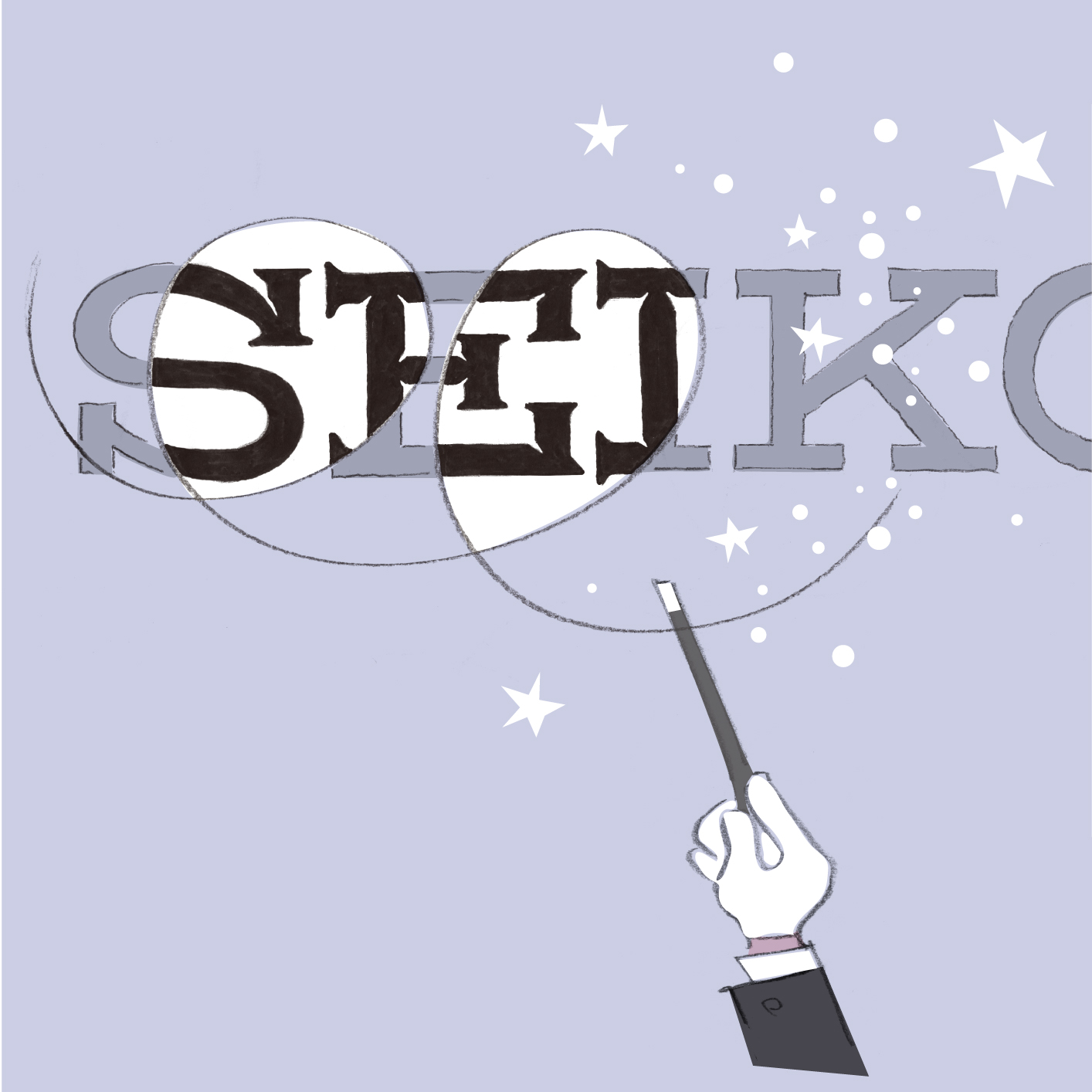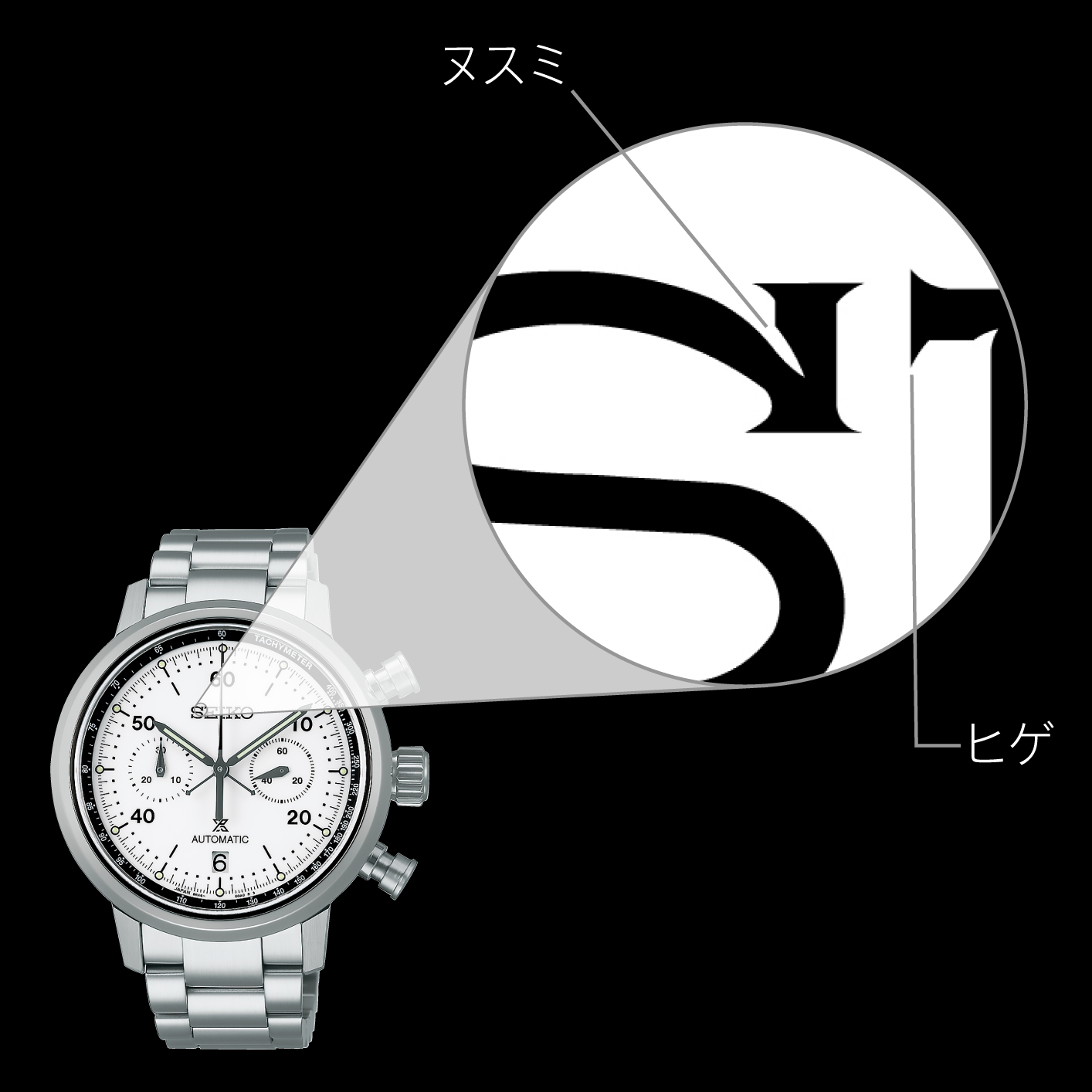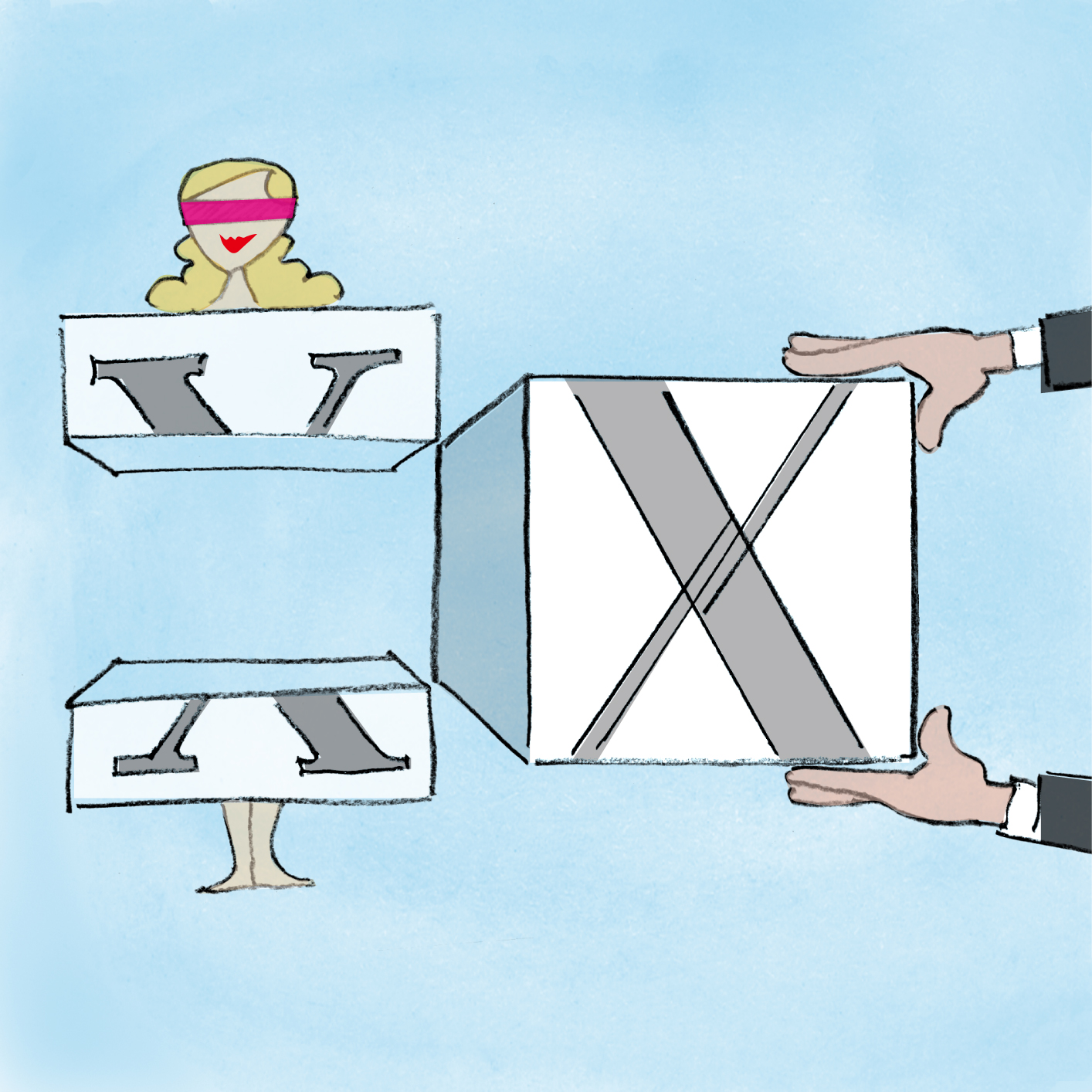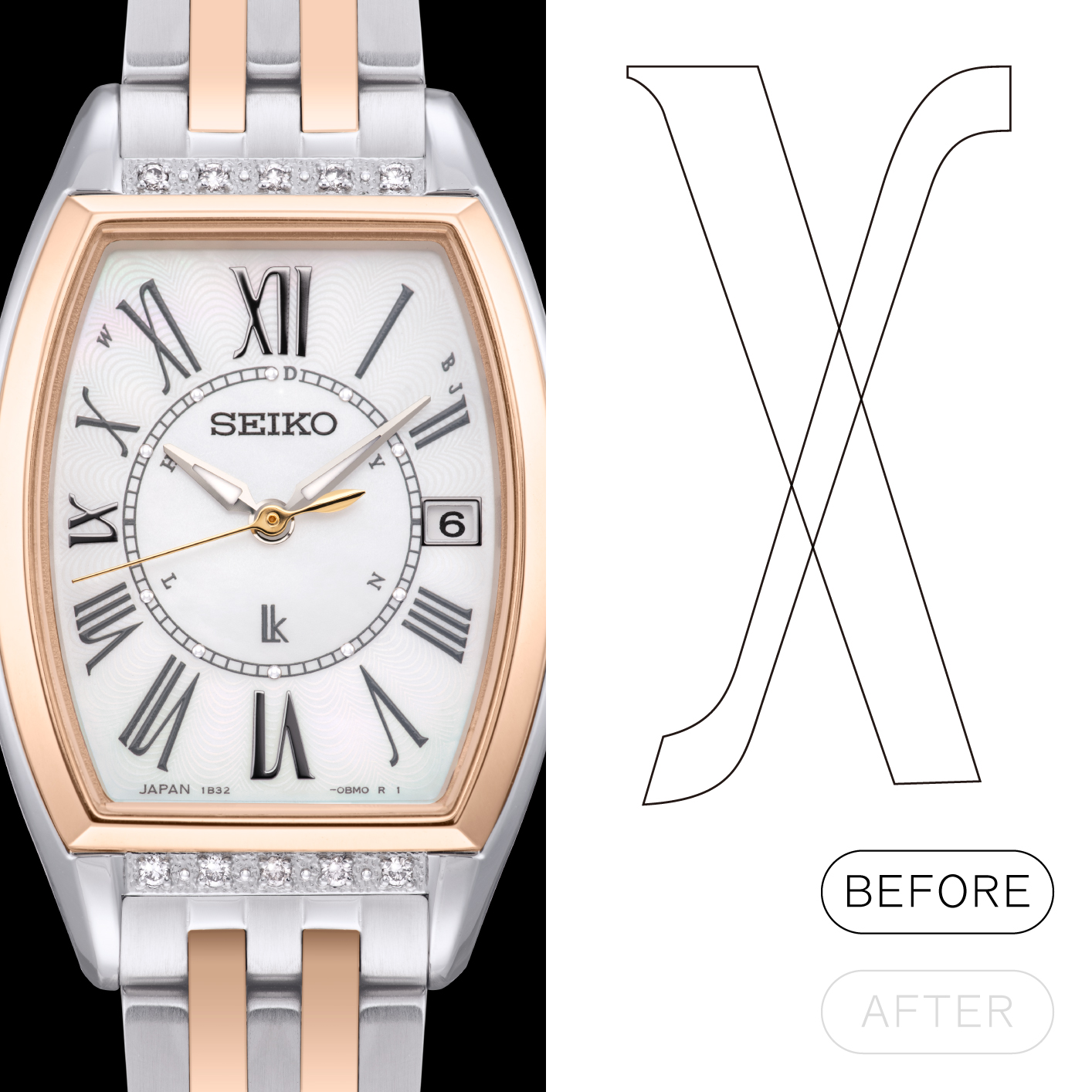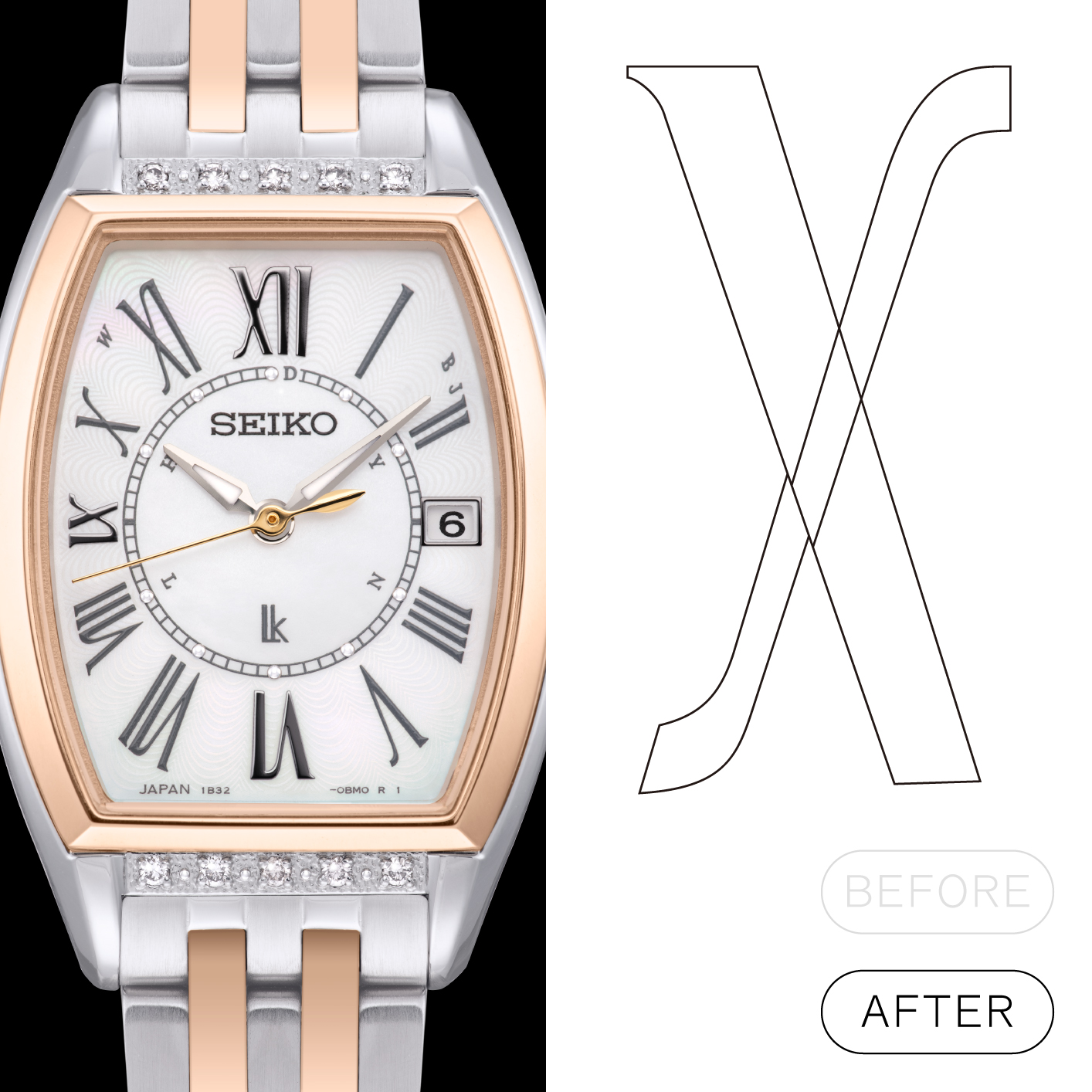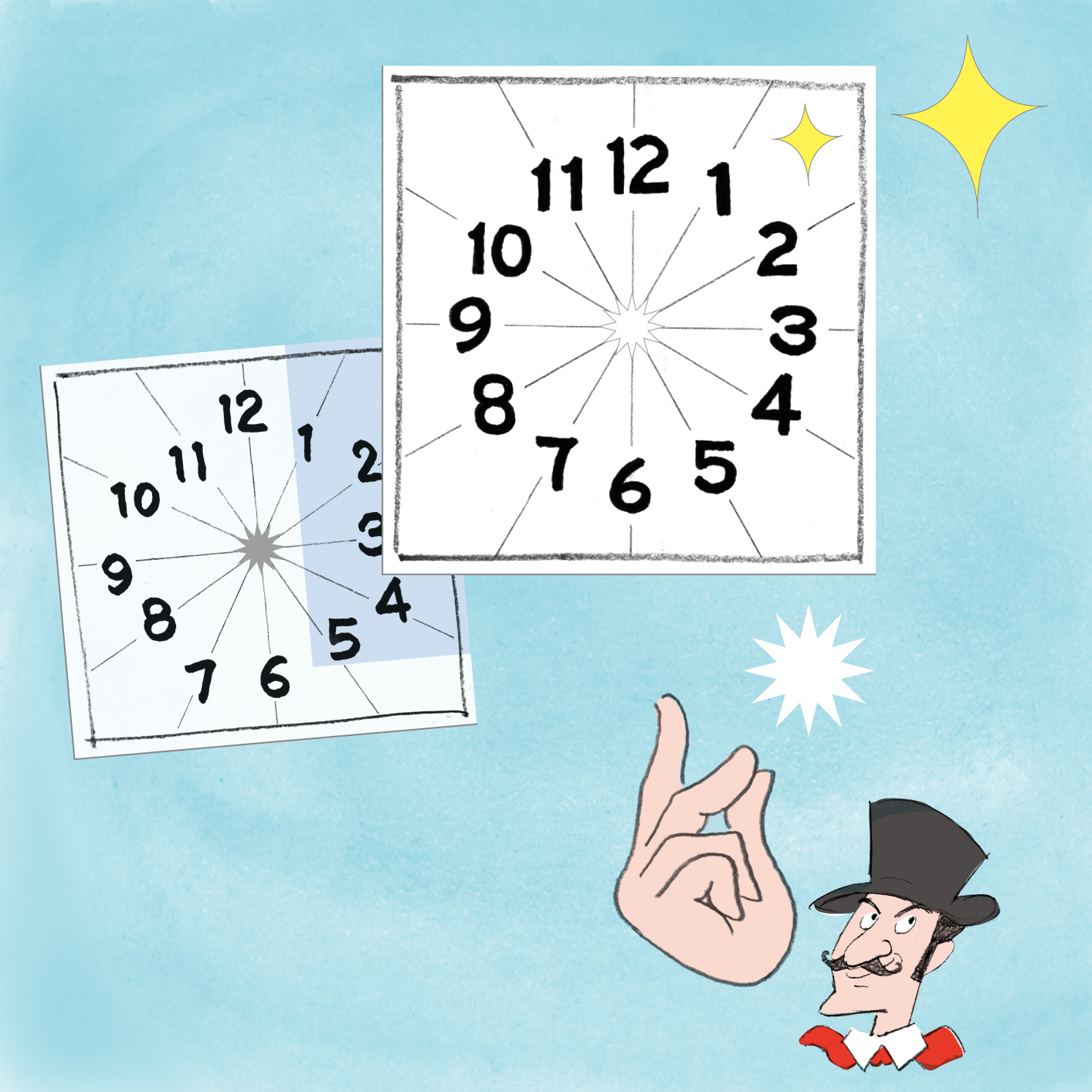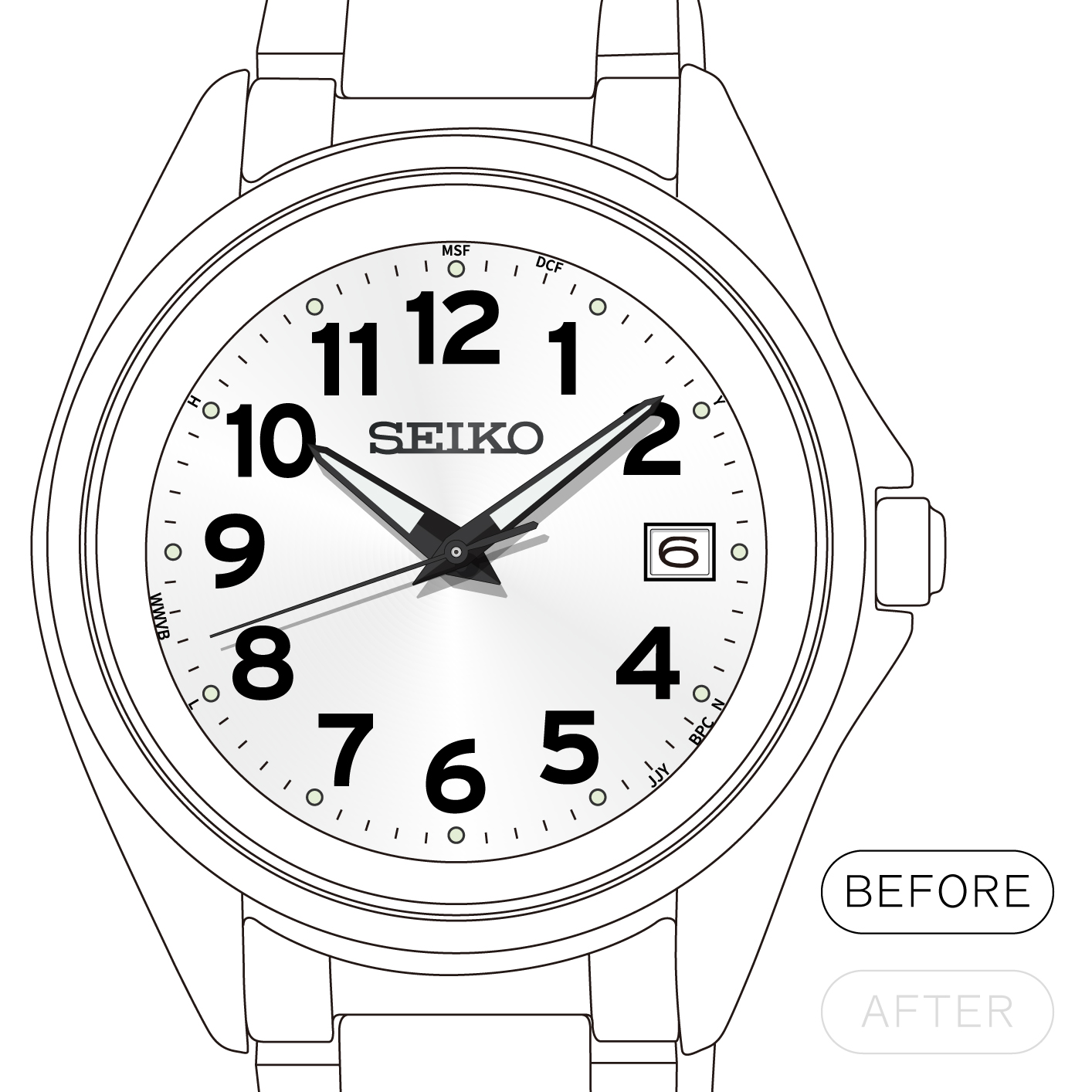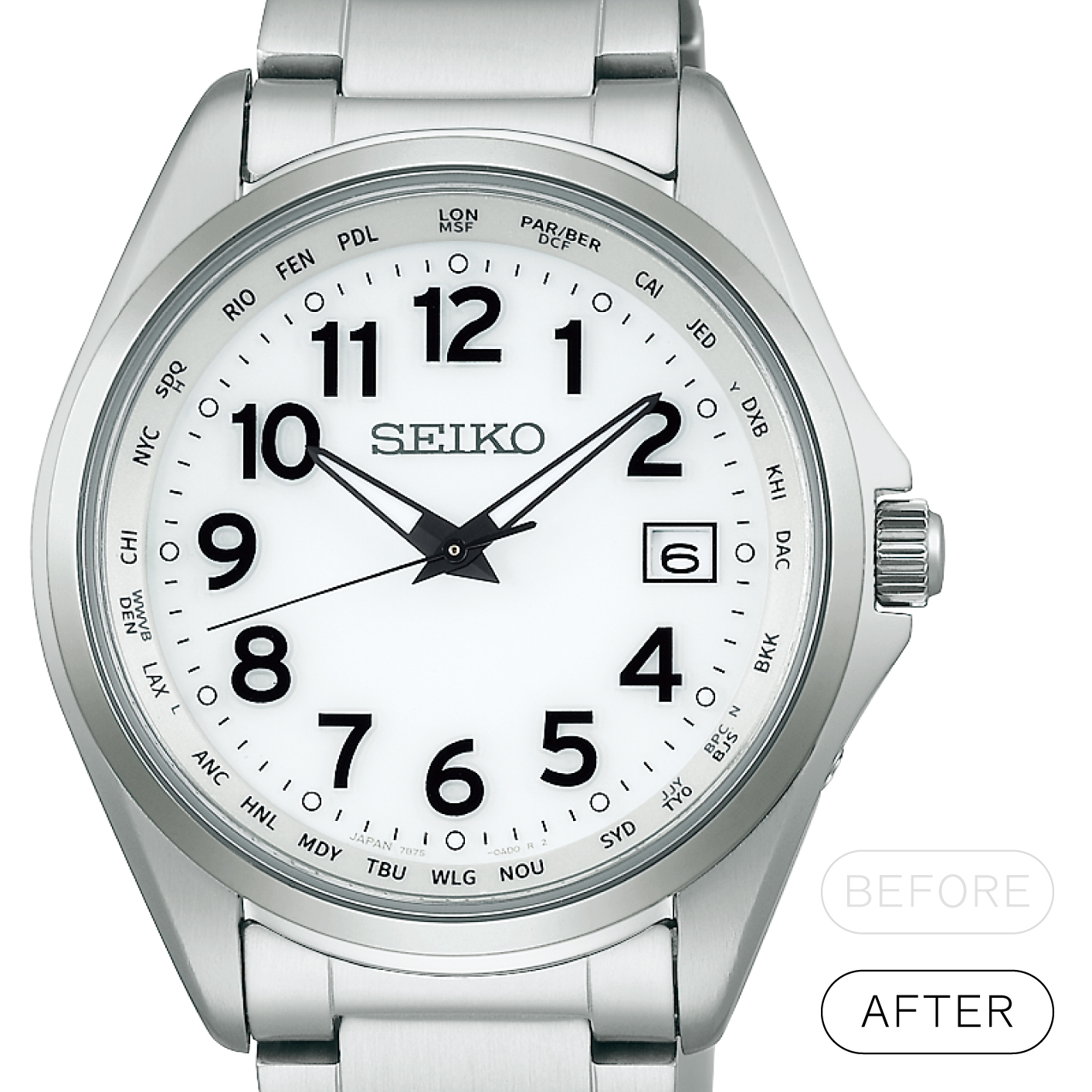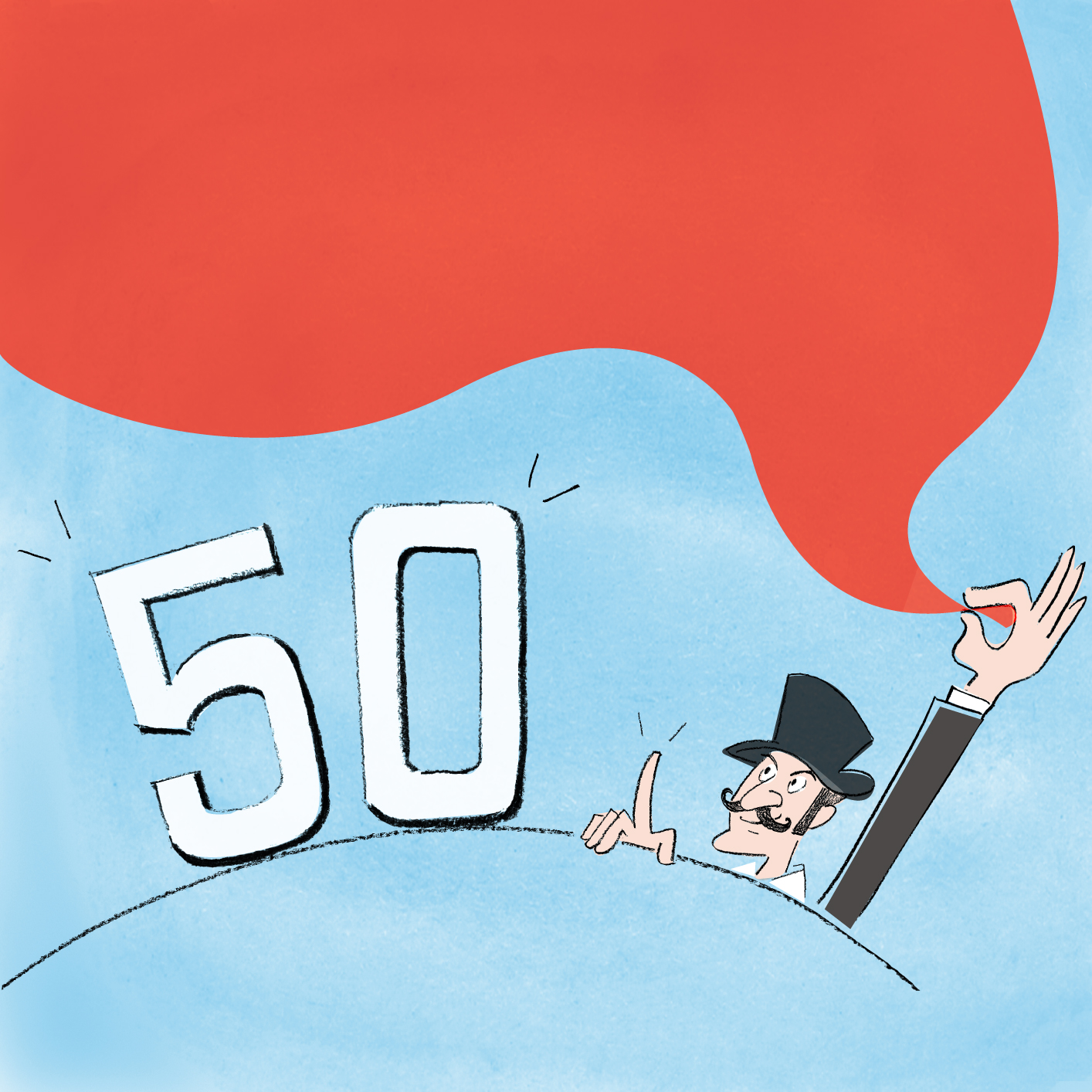
Vol.30 タネも仕掛けもございます。 「見やすさ」を支える、書体デザインの秘密。 Vol.30 タネも仕掛けもございます。 「見やすさ」を支える、書体デザインの秘密。
セイコーのウオッチのダイヤルをじっくりと眺めたことはあるだろうか。もっと言えば、ダイヤルに刻まれているインデックスや目盛りの形、さらには、そのインデックスがどういった場所に配置されているかに注意を向けたことはあるだろうか。毎日何気なく目にしている腕時計。その「見やすさ」を支えているのは、じつは書体デザインの「ある仕掛け」によるものだということは、あまり知られていないかもしれない。今回は、そのようなデザイナーの仕掛け(=技術的な工夫)の種明かしをしながら、書体デザインの知られざる秘密について紹介していきます。(2022.04.22)
セイコーの書体デザインの源流
そもそもセイコーのウオッチデザイナーの前身はダイヤルの版下職人や外装設計者でした。現在ウオッチデザイナーと呼ばれているような職種は、1956年に「生産部意匠係」として組織化した際の「意匠担当」に源流があります。それが国内初のウオッチデザイナーであったようです。
1900年から1950年代頃までのウオッチのケースは、スタンダードな2本かんのシンプルなデザインがほとんどでした。ムーブメントが定型だったためケースの構造・形状には差が少なく、バンドも店頭でユーザーが好きなストラップやブレスレットに付け替えることが多く、正規品には重きを置いていませんでした。だから必然的に、当時のデザイナーの仕事の多くは「ダイヤルデザイン」だったのです。
そんな歴史的背景もあり、セイコーのウオッチデザイナーには、ダイヤルへのこだわりがDNAとして受け継がれているのかもしれません。そこで今回は「違和感なく自然に見える」という目的のための、細部の「知られざる」技について、具体例を挙げながら詳しく見ていきたいと思います。
「見やすい文字」の、ヒミツの仕掛け
ウオッチの文字を見ていく前に、まずはブランドの顔となるSEIKOロゴを例に見てみましょう。Sの文字に注目してみると、文字の角が鋭く飛び出しているのがわかります。この部分を社内では「ヒゲ」と呼び、この処理を施すことで小さい文字でもくっきりと印刷できる効果があります。
また、縦線と曲線の境目に切れ込みのようなものが入っていることも確認できます。これは社内では「ヌスミ」といい、この処理を施すことで文字の角にキリッとした印象を与えることができます。
デザイナーは技術を駆使して、まるで魔法をかけるかのように心地よい視覚体験を生み出す。
拡大してみるとしっかりとヒゲがついているのが見て取れる。ヌスミについてもかなりの切れ込みが入っていることがわかる。
これらの技は数字にも用いられており、例えばドレッシーなウオッチによくみられるローマ数字には、よりエレガントな印象を持たせるねらいも込め、やや強めにヒゲをつけたりもします。たとえば、このルキアのローマ数字は「万年筆で書いたような」手書きの雰囲気を持たせるために、筆の運びの方向を意識して強めのヒゲをつけているのです。
そして、じつはローマ数字に見られる「X」の文字。この文字にも、おそらくふつうは気づくことのない仕掛けが施されています。その仕掛けは、クロスしている部分にあります。この「X」は細い線と太い線の交差でできているため、じつはそのままだと人間の視覚の特性上、ややズレているように見えてしまいます。そのズレを計算し、細い線が一直線に見えるような処理を施しているのです。ふつうに生活している中でこの仕掛けに気づくことはほぼ不可能でしょう。
細い線は、実は一直線ではない。種が分かればどうということはないこの小さな違いが、視覚体験には大きな違いをもたらす。
オリジナル書体がデザインされたルキア(SSVW180)。斜線の交差する部分をわずかにずらした補正をしているため、線は違和感なくまっすぐに見える。
「ふつうに見える」の、タネあかし
次に、文字の配置について見ていきましょう。ふつうに見えるということは、つまり「違和感がない」ということ。それをクリアする上で意識しなければならないのは、なんと言っても数字を12の分割の中に心地良く配置すること。ウオッチデザイナーは特に、円の形状と戦っていると言っても過言ではありません。
ここではアラビア数字のウオッチを例に見ていきます。やや間違い探し的ですが、若手デザイナーが最初に作成したレンダリングと、先輩デザイナーと共に更にそれをブラッシュアップし、最終的に商品化されたものを見比べてみてください。より心地良くアラビア数字が配置されていると思いませんか?違和感なくふつうに見える裏に、デザイナーの並々ならぬ努力と経験の積み重ねが隠れていることがわかりますね。
2枚のカードに描かれたダイヤル。一見するとどちらも同じに見えるが…。
ベテランデザイナーの助言により、わずかな違いであっても明らかに配置が整っていることがわかる。
また、回転ベゼルの表示板に配置されたアラビア数字にも仕掛けが施されています。このアラビア数字を取り出して、そのまま正体(せいたい)にしてみます。すると、2つの数字同士がやや外側に傾いていることがわかります。これも人間の目の錯覚で、アラビア数字を円周上にそのまま置くと、やや内側に、ハの字のように傾いて見えてしまうのです。その補正処理も、ふつうに見えるための欠かせないポイントのひとつなのです。
あくまでも自然に、手を加えているように見せない。それがプロの仕事と言えるのかもしれない。
わずかな数字の傾きを施しバランスのよい配置のプロスペックス(SBDC181)。お手持ちのウオッチを観察してみると、そこにも補正のテクニックが施されているかもしれない。
「そこまでやるか」な、錯視補正
せっかくですので、最後に「そこまでやるか」な錯視補正の例を見ていきましょう。ひとつ前に紹介した文字の配置は、ふつうに見えるための「なくてはならない」処理です。一方、最初に紹介した「ヒゲ」や「ヌスミ」は、より見やすくするための、いわばデザイナーのこだわりとも言えます。それが顕著に現れている例がグランドセイコーのモデルにあります。
このSBGC244を見てみると、ダイヤル上のアラビア数字だけでなく、ベゼル上の数字にもヒゲがついていることがわかります。さらには、ダイヤルリングの目盛り一つひとつにもヒゲをつけてあるこだわりよう。実際の商品を見るとその効果はかすかに感じられる程度ですが、ここにはグランドセイコーのクロノグラフらしい、研ぎ澄まされた佇まい、精緻感が表現されています。「最高のふつう」を体現する、グランドセイコーの使命感のようなものが感じられます。
用意の周到さ、細部への心配りが完成度を上げる。手品も、ダイヤルのデザインも。
ベゼルのアラビア数字はもちろん、サブダイヤルのアラビア数字にまでヒゲの処理がされている。「神は細部に宿る」を体現するモデルの一つと言えよう。(SBGC244)
使命感といえば、計測器としてのウオッチを追求した、プロスペックス SPEEDTIMERシリーズにも強い使命を感じます。SEIKOの文字にはしっかりとヒゲ、ヌスミが施され、数字や秒目盛りは最適な距離感とボリュームを考えられた配置になっています。また目盛りには細かな「線」だけでなく「点」も採用。記録を正確に計測するために、視認性と判読性をできる限り高めています。正確さが求められるプロスペックスだからこその「そこまでやるか」。というより、この場合「そこまでやるべし」なのかもしれません。
左のプロスペックス(SBEC007)は計測機器としての判読性を重視したデザイン。1954年に開発された高精度ストップウオッチ(右)から、そのデザインの思想は脈々と受け継がれている。
ウオッチデザイナーの研鑽はつづく
このような「ふつうに見えること」の裏に隠されたさまざまな仕掛けは、これまでのセイコーの歴史の積み重ねによって磨かれてきました。その中には、ルール化・定石化されているものもありますが、それをさらに進化させ、ウオッチデザインの可能性を広げるために、デザイナーは日々腕を磨き続けています。
若手デザイナーはもちろん、長年勤めているベテランのデザイナーでさえ、ウオッチをデザインする中で日々新しい学びや発見があります。デザインの進化に終わりはありません。それがデザイナーの試練であり、また醍醐味でもあるのです。
当たり前のように見える、そう見せる技術の習得は、何を隠そう、日々の努力の賜物である。そしてその研鑽に終わりはない。